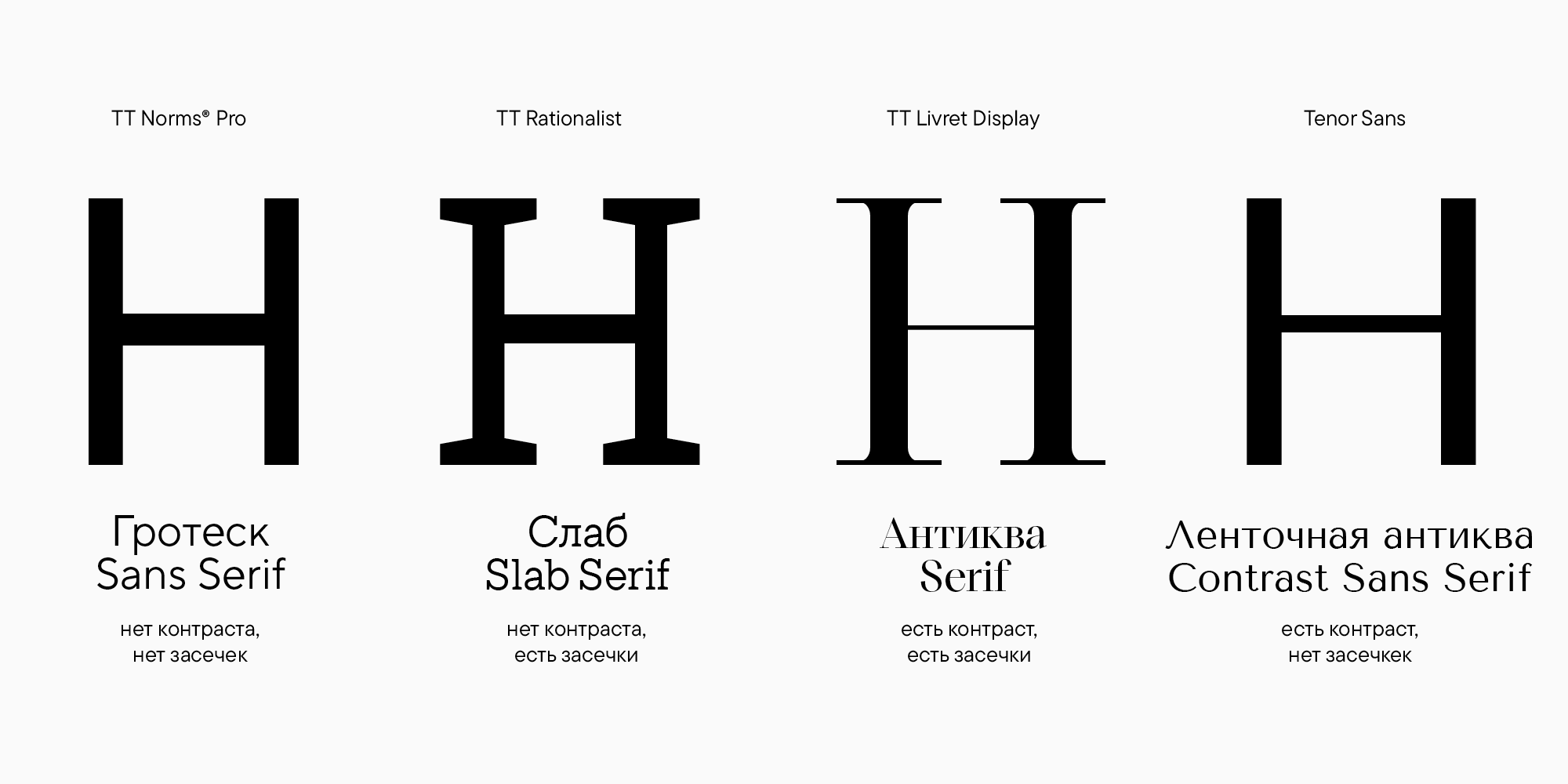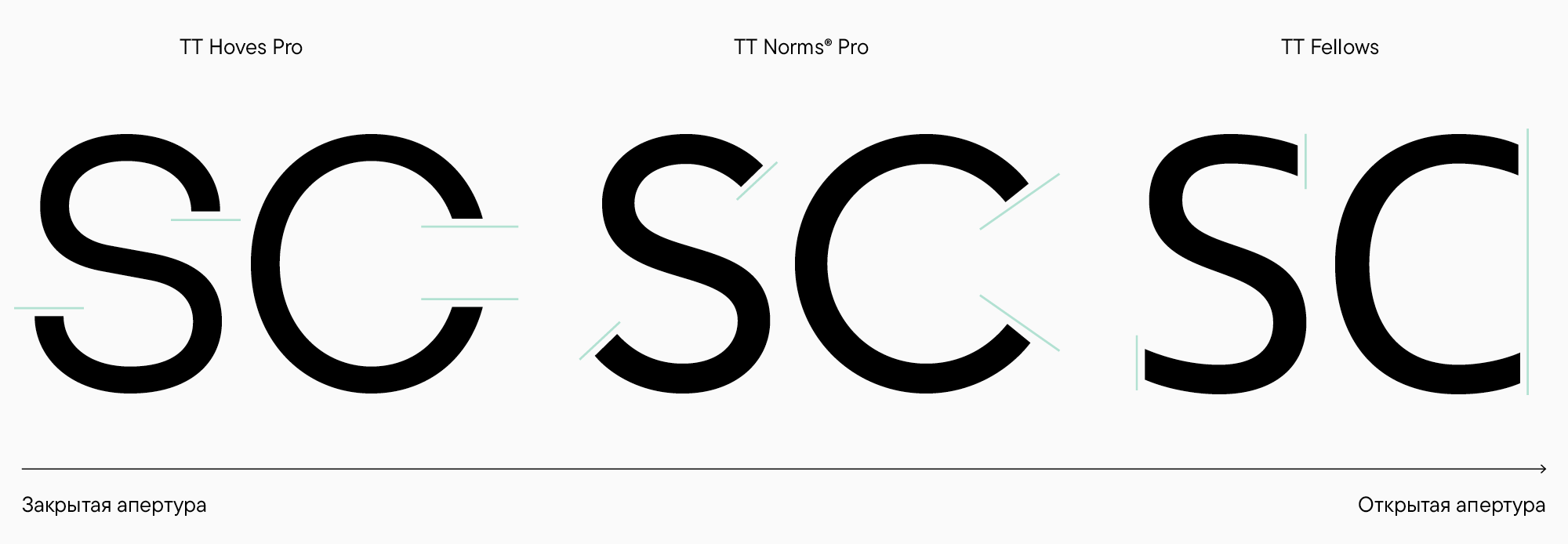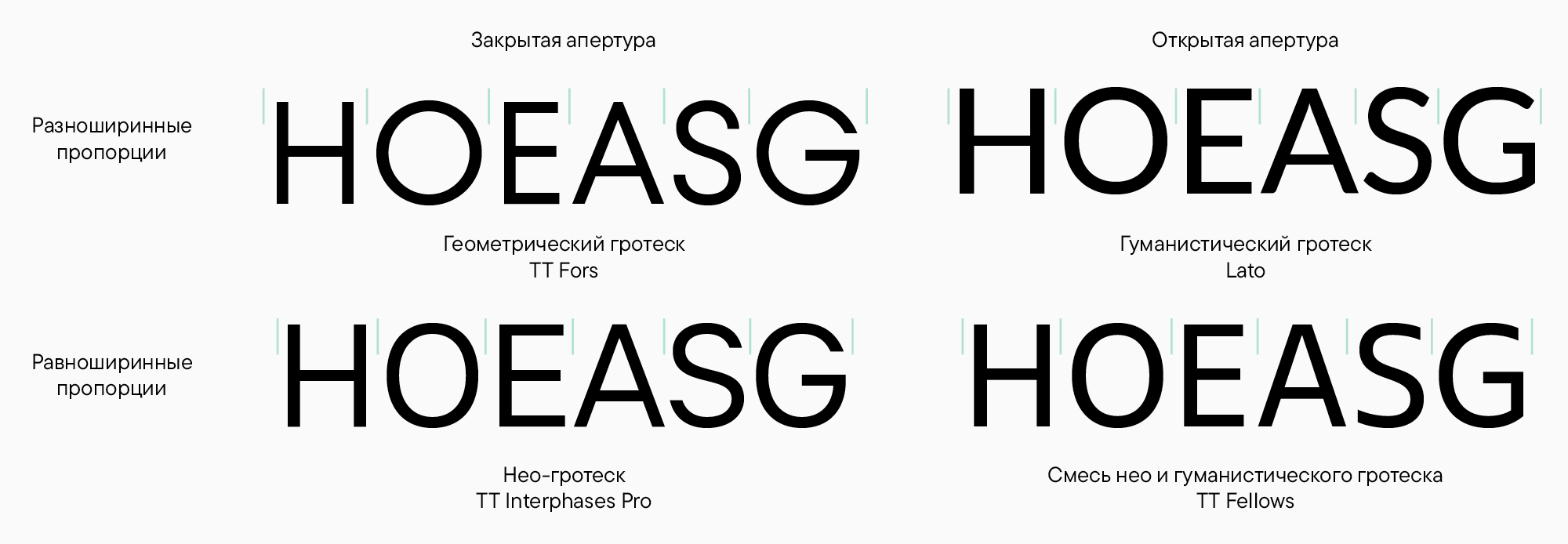
Создание шрифта — это сложный и кропотливый процесс, требующий большого опыта. Однако и работа с готовым шрифтом может быть не менее сложной. Нас очень часто спрашивают о том, как лучше использовать ту или иною гарнитуру и с чем ее сочетать. Мы помогаем клиентам выбрать самое подходящее шрифтовое решение для проекта: подбираем гарнитуры из нашей коллекции или создаем шрифт с нуля. И в этой статье мы поделимся с вами нашим опытом.
Юлия Гонина, арт-директор TypeType и автор таких семейств, как TT Livret, TT Fellows, TT Autonomous и TT Ricordi Todi, расскажет о том, как подбирать шрифты для проекта и как сочетать их между собой. А еще мы обсудим, зачем вообще нужно сочетать шрифты, разберемся в основных шрифтовых понятиях и подкрепим теорию примерами.  А в конце Юлия поделится несколькими полезными ресурсами, которые она использует в своей работе.
Зачем сочетать шрифты?
Для начала давайте ответим на вопрос, обязательно ли использовать несколько шрифтов в проекте или можно обойтись одним?
По правде говоря, отличных результатов можно добиться, используя только шрифты из одного семейства. И даже с помощью лишь одного шрифта получится создать интересную работу. Хороший пример — сайт Elisava Barcelona School of Design and Engineering, на котором мы видим всего одно начертание шрифта. Выглядит это очень стильно.
Резонный вопрос — если можно обойтись одним шрифтом, зачем сочетать несколько?  Во-первых, с помощью разных шрифтовых семейств можно добавить проекту эмоциональной и графической глубины, как если бы мы, например, сочетали различные цвета и материалы в одежде.
Во-вторых, в проекте можно использовать разные начертания шрифтов. Самое очевидное — брать разные варианты для заголовков и текстовой части.
Также с помощью разных шрифтов можно расставлять акценты и разделять смысловые блоки. А еще это очень хорошее упражнение, помогающее лучше понять, что такое шрифт и какое впечатление он оказывает на зрителя.
Шрифтовые понятия и характеристики
Прежде чем говорить о подборе и сочетании шрифтов, давайте пройдемся по основным шрифтовым понятиям. Если вы уже не новичок и знакомы с классификацией и терминологией, можете смело пропускать этот раздел.
Сначала посмотрим, какие шрифты бывают.
Можно выделить четыре основных типа:
1. Если в шрифте нет контраста, то есть штрихи выглядят одинаковыми по толщине, и нет засечек — перед вами гротеск;
2. Если появились засечки, но контраста все еще нет или почти нет — это слаб;
3. Есть засечки и заметный контраст — значит, вы смотрите на антикву;
4. А если у антиквы убрать засечки, при этом оставить контраст, получится ленточная антиква.
Сейчас самый распространенный тип шрифта — это гротеск, а второе место занимает антиква, так что в этой статье мы в основном будем рассматривать их. Однако видов шрифтов, конечно, существует намного больше. Подробную классификацию вы найдете в нашей статье «Классификация шрифтов».
Еще одна характеристика, на которую стоит обращать внимание — насколько открытая или закрытая у букв апертура. Чтобы понять, что это такое, посмотрите на левый и правый примеры. Так, буква «С» слева хочет сомкнуться, а справа, наоборот, открыться как можно больше. И, конечно, между крайними положениями может быть много промежуточных вариантов.
Чтобы углубиться в классификацию, можно объединить открытость с еще одним важным параметром — пропорциями шрифта. Круглые, прямоугольные и треугольные знаки в шрифте могут быть разной ширины. Мы видим на верхних примерах, что «О» и «А» заметно шире, чем «Н», «Е» и «S».
Также знаки могут стремиться к тому, чтобы быть одинаковой ширины, как на примерах ниже.
Так при сочетании пропорций и открытости получаются разные виды шрифтов или классификационные группы (если, конечно, сильно упрощать классификацию). Среди гротесков основными видами будут: геометрический (с круглыми геометричными овалами, подчеркнуто закрытой апертурой), гуманистический (с похожими на геометрический гротеск пропорциями, но имеющий рукотворный человечный характер и открытые формы) и нео-гротески (самые нейтральные из всех, имеющие ровный равноширинный набор и средней закрытости апертуру). Конечно, в современных шрифтах можно найти разные промежуточные варианты, например, равноширинные пропорции нео-гротеска, скомбинированные с гуманистической открытой апертурой.
Стоит также обращать внимание на формы знаков. Они могут заметно отличаться, влияя тем самым на характер шрифта. Посмотрите, например, на мягкие двухчастные «а» и «g» в гуманистическом гротеске и сравните их с четкими, звеняще круглыми формами одночастных «а» и «g» в геометрическом гротеске. В нео-гротеске здесь очень характерная форма «R» и терминалов в «g» и «y». Но этот пример гротеска, помимо прочего, отличается от остальных общей нарочитостью форм, поэтому я бы назвала его дисплейным или акцидентным, то есть харАктерным шрифтом для крупного размера.